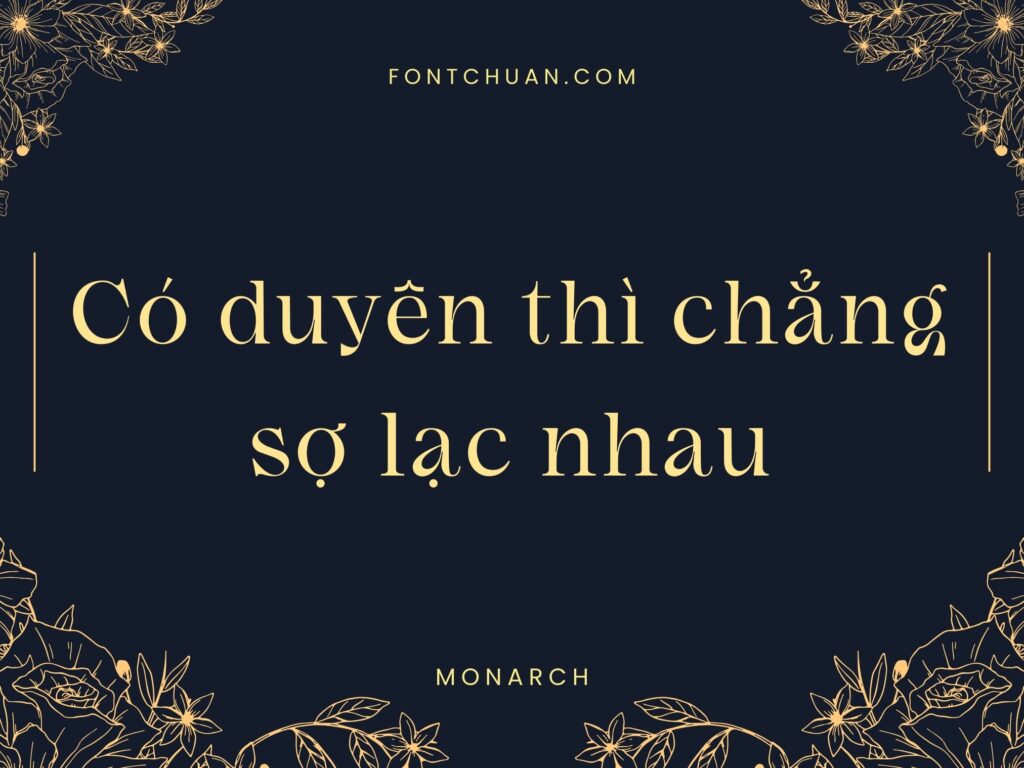
Font Monarch Trọn Bộ Font Tiếng Việt
Monarch là một font serif trang trí được thiết kế bởi Vladimir Nikolic. Với các phiên bản như Regular, 3D, Shadow Filled và Shadow Gradient, Monarch mang đến sự đa dạng và sáng tạo cho các dự án thiết kế. Nhờ phong cách tinh xảo và tính ứng dụng linh hoạt, Monarch thường được xem là một trong những Font chữ thiệp cưới đẹp mắt, giúp các mẫu thiệp trở nên sang trọng và lãng mạn hơn. Font này miễn phí cho sử dụng cá nhân và có sẵn trên các nền tảng như 1001 Fonts và DaFont. Monarch hỗ trợ nhiều ngôn ngữ, được sưu tầm và đăng bởi thành viên của Font Chuẩn.
Font có thiết kế độc đáo với các nét chữ trang trí, tạo nên sự nổi bật và thu hút trong từng chi tiết. Với vẻ đẹp cổ điển pha chút hiện đại, Monarch cũng được đánh giá cao như một Font chữ bất động sản nhờ khả năng thể hiện sự đẳng cấp, sang trọng và đáng tin cậy trong các ấn phẩm giới thiệu dự án hay thương hiệu.
Font có thiết kế độc đáo với các nét chữ trang trí, tạo nên sự nổi bật và thu hút. Monarch phù hợp cho các thiết kế tiêu đề, poster, logo và các ấn phẩm truyền thông. Các ngành nghề như quảng cáo, thiệp cưới, giáo dục và bất động sản có thể tận dụng hiệu quả font này. Ngoài ra, Monarch cũng thích hợp cho các sự kiện như lễ hội, sinh nhật, ngày Nhà giáo, Valentine, và có thể sử dụng như một Font chữ Giáng Sinh để trang trí thiệp, poster hay banner mùa lễ hội, mang đến không khí rộn ràng, vui tươi và ấm áp cho các sản phẩm thiết kế.